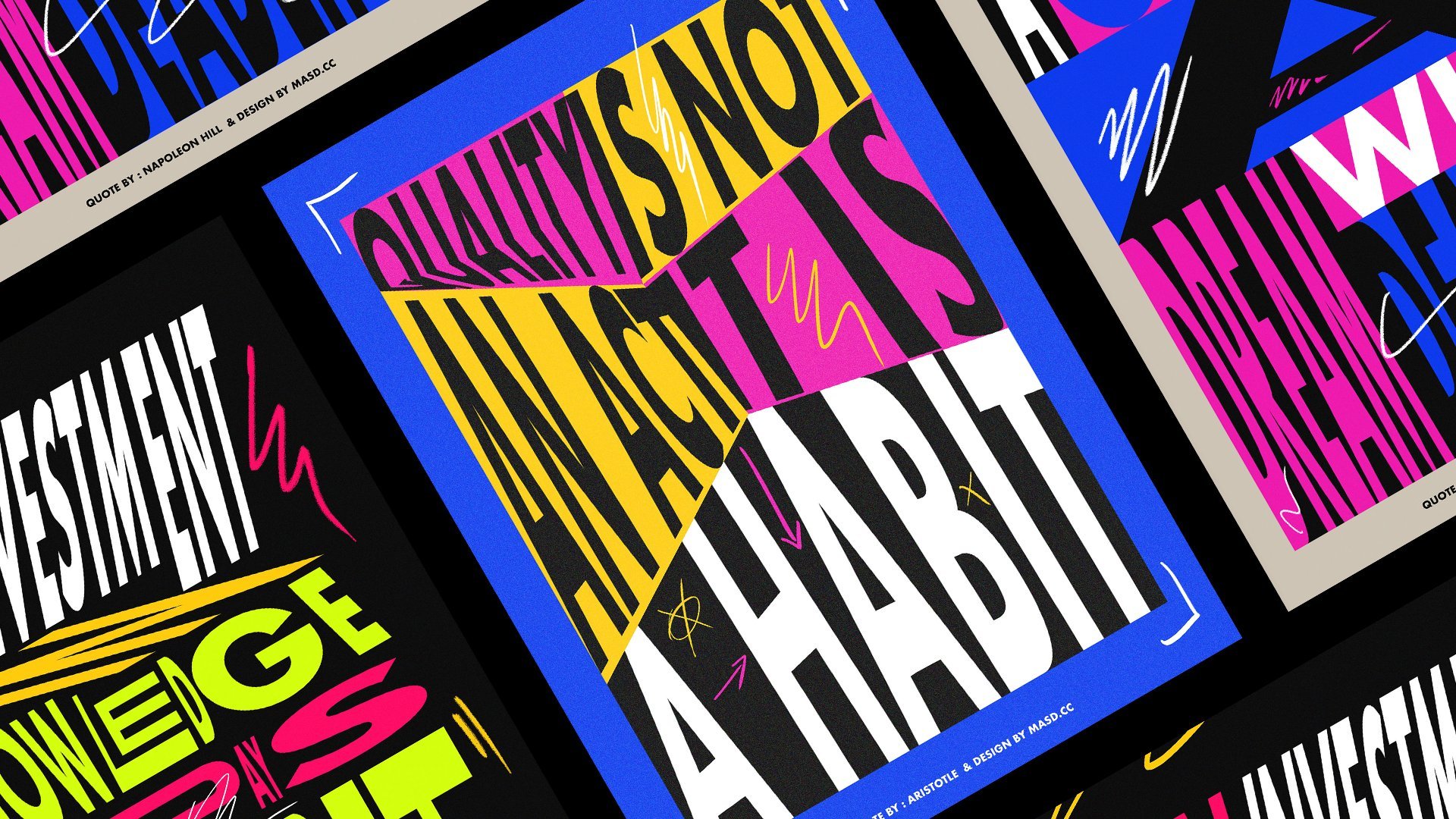
Conception d'affiches en typographie contemporaine
Introduction de classe - Inspiration et référence de style
Leçon 01 : Conception de la première affiche - Déformation typographique et composition de grille de base
Leçon 02 : Compostion menée par typographie - distorsion typographique individuelle
Leçon 03 : Composition d'affiche dynamique - Composition à base de distorsion et de forme d'enveloppe
Leçon 04 : Éléments de conception et post-production finaux dans Adobe Photoshop
Aujourd'hui, nous allons concevoir ces 3 affiches de typographie contemporaine différentes,
La plupart du design sera réalisée dans Illustrator en utilisant 3 techniques et approches différentes du design, puis quelques touches finales et concevoir quelques détails sur le photoshop
1. Bande-annonce du cours: Bonjour tout le monde. Je m'appelle Marcus, animateur animateur. Aujourd'hui, nous allons concevoir ces trois affiches typographiques contemporaines différentes. La majeure partie de la conception sera réalisée dans Illustrator en utilisant trois techniques différentes et trois approches différentes de la conception. Et puis nous ferons quelques touches finales et l'entonnoir. Ce sont des détails dans Photoshop. Je suis presque sûr que vous allez avoir du plaisir à faire ce tutoriel. Et je suis sûr que vous allez avoir de nouvelles techniques à mettre sur votre manche. Alors n'oubliez pas de vous inscrire et de me rejoindre en classe. 2. Introduction du cours - Inspiration et référence du style: Bonjour à tous et bienvenue à la première leçon. abord, je voulais juste partager avec vous d'où j'ai eu cette inspiration. C' est en fait ces affiches. J'ai eu ça. Je les ai vus sur Pinterest et ensuite je suis allé regarder. Qui était le designer qui a commencé ce genre de style. Et parce que je pensais que c'était vraiment cool et je voulais vraiment expérimenter avec ce titre aussi. J' ai donc aimé quelques affiches remplissant ça, faisant ce style. Et je voulais juste partager avec vous le portefeuille de designers. Il s'appelle Chris Andrew petit et c'est notre designer australien. Et dès que j'ai vu son travail, j'étais comme fasciné par l'utilisation de la typographie. Je n'aime pas la dernière, je crois, depuis un an environ. J' ai été obsédé par le travail de typographie. J' ai vu tellement de contenu sur Instagram à propos de la topographie cinétique ainsi que de la topographie mobile et de nouveaux types d' ondes pour utiliser la typographie normalement comme je l'ai fait avant la classe, comme la typographie, j'ai senti un elifs légers comme dans le monde du design vit dans un très, dans une sorte de strict vers comme monde sérieux. Et quand je vois quelqu'un faire, je m'amuse tellement avec la typographie et je fais vraiment si beaux dessins et je ne fais que briser toutes les règles. Comme, comme obtenir un type et juste déformé comme ça. Et expérimentez avec des couleurs et des contrastes entre les formes. Et puis il suffit de créer cela comme des compositions intéressantes avec elle. J' étais juste fasciné par son travail et j'ai juste décidé d'explorer un peu pour moi-même, quelques pauses tombant ce style peut-être essayé d' obtenir des connaissances sont libérées aussi parce qu'il Arctic est comme, n'est pas comme ça est correct de s'inspirer et parfois même de copier d'autres. Les gens, les designers travaillent parce que vous prenez comme vous avez essayé de recréer quelque chose. Vous avez essayé d'entrer dans l'esprit de cette personne et d'essayer de voir ce qu'elle voit. Et ce ne sera jamais le même parce que vous aurez toujours votre propre contribution à ce sujet. Ce n'est pas comme si je créais Saclay, celui-là. Maintenant, vous allez juste utiliser le même type de style, mais ce ne sera jamais la même voix parce que c'est unique pour vous, comme votre approche sera différente. Donc, il est correct si vous vous inspirez juste où d'autres personnes, je suis sûr que Chris, Andrew Coats inspiré par certains quelque part aussi bien. Tout comme un mélange de respirations et je voulais juste partager avec vous c'est le portefeuille d'abord parce que je pense que c'est vraiment, je ne pense pas que vous devriez le vérifier. Et je pense que c'est incroyable. 3. Leçon 01 : Concevoir la première affiche - distorsion et composition des mailles: Je vais donc montrer d'abord que les journalistes que nous allons concevoir. Donc, la conception finale sera sur un magasin. En fait, c'est comme les formes vectorielles. Et le premier que nous allons commencer est celui-ci. Une autre chose que je voulais partager avec vous est que j'ai créé une bibliothèque pour ce cours, va être sur vos fichiers Skillshare. Veillez à télécharger la bibliothèque. Vous aurez les couleurs et l'illustration réelle. Et pour cela, vous allez juste dans les bibliothèques ici. Si vous n'avez pas l'onglet de la bibliothèque ici, vous pouvez simplement aller à Fenêtre et essayer de trouver vos bibliothèques ici. Et puis nous allons juste à la bibliothèque d'importation. Sélectionnez la destination de votre bibliothèque. J' ai déjà sauvé le mien ici. Donc vous allez avoir ce fichier dans le dossier. Et dès que nous avons importé, il vous suffit de cliquer sur ouvrir et d'importer. Et tu auras toutes les couleurs que j'utilise sur ces affiches. Et les affiches réelles et réelles au cas où vous voulez les ouvrir et juste jeter un coup d'oeil. Si vous cliquez et glissez et déposez comme ceci, vous allez simplement le déposer. Si vous voulez aller à l'intérieur du vecteur, vous pouvez simplement sélectionner Intégrer. Et puis nous allons juste incorporer l'illustration ici et vous pouvez simplement dissocier puis relâcher le masque d'écrêtage. Et tout ce que vous avez maintenant est un fichier vectoriel. Et vous avez juste besoin de libérer les masques d'écrêtage jusqu'à ce que vous ayez réellement toute la capacité du fichier. Eh bien, commençons notre première affiche pour cette école de droit à nouveau. Nous allons vous montrer que cette résolution va réellement la rendre verticale 358 par 4961. C' est plus ou moins comme une affiche A3. Alors donnons juste un nom à cette affiche de Skillshare. Un. Et appuyez sur OK. Je suis désolé si je parle probablement trop vite. J' essaie de ne pas faire attendre trop longtemps cette classe. Je ne sais pas. J' ai l'impression que parfois j'aime être comme le grenier est plus dynamique si l'enseignement est encore tapé à la vitesse et ne prend pas trop à ces employés ou expliquer ou beaucoup trop lentement. J' aime le garder, reste génial moi-même engagé dans la classe. Donc, pour ces classes, j'utilise en fait quelques citations inspirantes d'un Moyen-Orient en fait, et je dois partager cela sur des fichiers sous. Et DC était comme quelques appels d'inspiration à l'avant, même des proverbes chinois, deux philosophes aux musiciens, aux intrapreneurs actuels. Et c'est comme je le fais, je fais la loi, je pense que c'est comme si il y avait beaucoup de pouvoir dans ces codes. Et parfois je les lis et ils font est comme Orozco pour moi. Parfois, je les lis et ils m'inspirent ou ont du sens à ce moment-là. J' aime donc en lire un au moins par jour et j'aime les utiliser autant que possible pour mon travail personnel, qui était ce que j'ai fait dans ces affiches. Donc le premier que vous allez utiliser vient d'un tas de Napoléon Hill. Et un objectif est un rêve avec un délai parce que vous ne voulez pas ce fichier. Ce sera dans le dossier Skillshare. Sélectionnez l'un de ces codes comme vous le souhaitez. Est-ce que j'ai essayé de ne pas utiliser de très longs parce qu'il vous donnera plus. Vous pouvez sélectionner aussi longtemps que vous le souhaitez. Mais plus vous avez de mots, plus vous aurez besoin de temps pour exposer chaque mot, ce qui pourrait être des meubles comme vous avez plus à expérimenter par tous, essayez juste de l'utiliser comme un très court pour l'instant. Et peut-être après avoir fait ce cours, même si vous faites ce type de style à nouveau, vous devriez explorer comme attendre plus longtemps pour sûr. Donc je vais utiliser celui-là. Je vais juste copier et coller ceci. Et je vais utiliser l'outil de texte dans Illustrator pour juste coller l'échelle de coin. Un rêve est un objectif. Un objectif est un rêve avec une date limite. Belle visite. Je vais en fait utiliser en fait un très bon, comme une cabine VLC de l'éthique est une police qui fonctionne comme vous le feriez n'importe quoi. Et quand je ne suis pas sûr du type de police que je vais utiliser pour n'importe quel projet. Et s'il est comme un projet client, 90 pour cent des fois ils auront déjà une police. Mais s'ils n'ont pas, je vais aller à sera vétérinaire soins ou coton ou pour la tournée. Et je vais juste aller au personnage ici. Et je vais tout faire. Donc, la première chose que vous devez faire est d'étendre vos tests, votre texte. Assurez-vous que vous êtes satisfait du code. Parce que dès que nous développerons cela, nous ne pourrons plus éditer le texte. Si vous voulez peut simplement faire une copie de cela, peut-être aller à modifier. Copier, Modifier, Coller. Laissez juste ici pour la sécurité au cas où vous voulez changer cela pour une raison quelconque ou changer la police. Alors commençons. Allons à Objet et allons à Développer. Appuyez sur. Ok, parfait. Donc le truc dans le style que j'aime le plus, c'est les laiteries, pas de règles sur la façon dont vous traitez sa police. Vous pouvez l'étirer vers le haut ou vers le bas. Vous n'avez pas besoin d'aimer, vous savez, quand vous concevez, vous devez vraiment être à la recherche du crénage et essayer de faire sens de la distance et tandis que les proportions et genre, c'est tellement ennuyeux parfois . Et le style est tout, mais pas une erreur ennuyeuse. Donc, la façon dont j'aime le faire est juste, commençons par séparer les mots. Un but est un rêve. Date limite. Super. Ainsi, vous pouvez en fait, si vous le souhaitez, vous pouvez commencer à créer des formes en premier. Et comme nous allons utiliser l'outil Rectangle, par exemple. Et juste essayer de créer des formes comme nous avons commencé, aléatoires. Vous n'avez pas besoin de suivre les notes. Nous pourrions faire une grille et suivre la grille, mais c'est pour être aussi libre que nous, comme nous le pouvons. Je pense que si vous pouvez tous le lire en tant que designer, nous avons déjà beaucoup trop de règles. Donc, nous allons savoir qu'il y a des règles ici et pas de grille du tout. Alors allons-y. Vous pouvez juste aller à la lumière que vous élaborez, tenir à juste important et utiliser mes couleurs si vous voulez. Sinon, vous pouvez simplement aller aux nuances de couleurs ici. Trouvez une très belle nuance pour votre affiche. J' aime le pape déchiré par la guerre. Et vous pouvez simplement explorer toutes les couleurs étonnantes qui se trouvent déjà dans les bibliothèques d'Illustrator. Ou vous pouvez simplement aller aux équipes de couleur et essayer de trouver une couleur vraiment agréable pour lui et juste utilisé à elle. Ne vous sentez pas obligé d'utiliser mes couleurs. S' il vous plaît, assurez-vous que vous l'êtes. Vous explorez en fait plus de couleurs et je vais essayer de ne pas passer beaucoup trop de temps sur les couleurs sur cette classe parce que je voulais faire une charge. Et, mais et je suis sûr que vous pouvez simplement utiliser cet explorateur sur la couleur, Adobe Color Thèmes sera, vous êtes prêt à aller. C' est une sélection incroyable ici. Je vais juste fermer ça pour l'instant. Alors commençons. Donc, vous pouvez juste commencer comme je l'ai dit, comme juste bloquer quelques formes autour et ensuite utiliser vos textes. Ils sont comme, je pense à peut-être comme cette forme noire ici. Je vais à la commande C, commande F pour coller en place. Je vais le faire utiliser cette couleur rose ici. Et maintenant je vais me faire perdre mon premier mot. Je vais faire ça large. Choisissons ce solide noir parce qu'il est devant une lettre et je vais l'arranger et le vendre à dos. Et ils vont utiliser cet outil de distorsion ici, l'outil de transformation libre. Si vous cliquez sur E, il suffit de vous pousser vers le haut. Ici. C'est, ça fait du bien de faire ça. Pour une raison quelconque. Si mes directeurs artistiques, certains font ça à notre, dans notre travail, elle va juste se montrer, juste me tuer. Je ne peux pas faire ça avec des polices. Mais le truc, c'est que, je pense qu'on devrait avoir le temps de jouer. Je pense que c'est quand vous arrêtez de jouer et de s'amuser avec le design est quand vous commencez, quand vous dites juste quand il commence à être juste un travail et pas comme un passe-temps ou comme en fait quelque chose que vous aimez faire ? Je pense que pour moi je n'ai pas joué pendant des années. Comme en tant que designer, je viens d'avoir du travail client et je l'ai fait a fonctionné parce que je ne sais pas, pendant longtemps sans faire d'expériences personnelles ou de projet personnel. Et je pouvais avoir l'impression que je n'étais pas Thai Wah commencer à haïr. Mais je commençais à ne pas profiter comme j'avais l'habitude de profiter de mon professionnel comme quand j'ai commencé. Donc, c'est un, Je vais juste faire glisser le but maintenant, faites un clic droit. Amenez-le à l'avant. Oui. Donc je pense que c'est important aussi pour vous, tout comme, vous savez, c'est important pour vous d'aller dehors et de vous promener dans la nature. Je pense que c'est important aussi, d'aller dehors sur Illustrator et juste avoir un, aller. Amuse-toi juste, tu sais ? Non, juste créer quelque chose. Ou même tout comme je l'ai fait, continuez comme sur Pinterest, trouvez quelque chose de vraiment cool et essayez de le recréer en quelque sorte et essayez d'en faire votre site, pour en faire votre style. Donc maintenant, comme je suis déformé est un peu, mais sur un but, je veux réellement commencer à déformer le briquet comme égal. Je veux en faire un peu plus. Peut-être que je vais faire l'un des distorsions individuelles comme. Au lieu d'être un groupe plus âgé. Comme ça. Peut-être que le o faire quelque chose comme ça. C' est peut-être que tu vas soulever cette jambe. Sont tous déformés encore plus qu'un, quelque chose comme. Donc, la première affiche, je veux juste demander d'explorer comme juste des distorsions d'échelle, pas comme autant de rotations. Et c'est comme un échauffement pour ce qui se passe ensuite. Donc un but est que je le ferai, je ne peux pas vraiment faire le simple, désolé que j'ai fait avant. Ça. Par exemple, je vous ai montré ici. Parce que c'est comme, ça, ça dépend vraiment du moment où vous faites ça. C' est comme chaque fois que vous allez faire ce processeur, il va recréer. Il aura un regard différent conçu de sorte que la technique sera certainement la même. Tout comme explorer les formes et les formes. Un but. Peut-être que vous pouvez simplement mettre à l'échelle ces jours-ci pour jouer avec le contraste liquide et la position ainsi. Tu sais, comme un but, tu n'en as pas besoin. Encore une fois, nous avons cette boîte ici pour, pour référence. Bien que nous le puissions, nous pouvons jouer avec la boîte autant que nous le voulons aussi. Vous n'avez pas besoin d'être trop précieux à propos de la boîte. Comme, encore une fois, nous ne voulons pas de grilles est comme des lignes directrices que nous ne pouvons pas suivre l'ère. Donc, un but est, nous allons juste faire maintenant est un but est un peu comme ça, mais sont en fait besoin de faire est de créer une certaine séparation entre les lettres. Sinon, on dirait qu'il est le même mot comme les gardiens de but, au lieu de deux moments différents du vocabulaire. C' est logique. Oh désolé, je viens d'utiliser un raccourci, mais vous pouvez simplement sélectionner la forme ici et organiser et envoyer à, vous avez le raccourci ici. Je vais juste envoyer à l'arrière et arranger. Envoyer à Retour. But est juste peut-être choisir, peut-être des changements trop larges. Peut-être que tu vas encore jouer avec la sphère de distorsion. S' il vous plaît assurez-vous de trouver comme obtenir comme un code vraiment sympa de cette liste et, et jouer autour. A vraiment envie de voir comme parce que je suis sûr que certaines personnes choisiront les mêmes codes pour. Vous pouvez même ajouter comme je l'ai fait en ce moment. Vous pouvez simplement ajouter de nouveaux éléments à leur police. Il n'y a aucune promesse. Erreur. Partez en disant que c'est comme si je suis sûr que certaines personnes choisiront le même, le même froid, l'outil Simcoe parle à différentes personnes. Et je veux vraiment voir comme, comment, comment allez-vous cela, comment vous le concevez, comment ce sera différent ou vous savez, comme comment quelque chose comme deux personnes peuvent avoir le même code et en raison de deux différents conçoit soigneusement. Et même le collège, je pense que les couleurs sur ces exercices sont si essentielles parce que c' est comme si vous jouiez avec le contraste et les formes et vous êtes certainement désordonné avec toutes les règles de la typographie. Mais la couleur aide aussi, comme aide le message beaucoup ici. Continuons à changer ça jusqu'à ce que ça se sente bien. La chose si un téléphone conçoit parfois c'est un peu comme si c'était un peu un sentiment. Parfois, c'est juste comme vous, vous sentez n'est pas encore là même quand ça a l'air beau. Continuons à pousser. Et puis est, alors vous date limite de ce qui est Est le fil est conçu et ce qui est l'art devient vraiment difficile à définir pour moi au moins. Parfois, je pense que le design est une combinaison de fonction et d'art. Et je ne sais pas si c'est une chaîne. Où est-ce ? Nike est blanc aussi. Peut-être que je vais déformer cette diapositive. Et encore une fois, vous, ceci, il s'agit juste d'expérimenter et de décharger tout. C' est comme si vous êtes un réalisateur, dit que c'est à propos de faire, ont vraiment faim ou Hey, je suis vraiment en colère. Comme quoi ? Ce que tu fais c'est l'objectif de décharge est correct, cool. Il suffit de pousser ça. Peut-être en fait, nous allons alors nous allons faire de cela un objectif est. Et puis peut-être que vous pouvez continuer à expérimenter jusqu'à ce que vous vous sentiez juste et que vous pouvez toujours revenir ici. Et la justice. Maintenant, nous allons juste utiliser l'échelle ici. Donc, c'est l'échelle d'utilisation. Oui, Donc, pour venir remplir plus mieux , celui-ci ici, c'est parfois difficile de jouer avec le contraste des formes aussi. Oui, je pense que tu penses que je suis content de ça. Et maintenant, rêvons. Donc jusqu'à ce que vous utilisiez le même style que j'utilise sur une première affiche, que j'utilise l'a pour remplir tout cet espace. Il crée une très belle forme. Et comme ce genre d'effet de flèche, ce qui est vraiment cool. Donc, je vais juste faire une nouvelle boîte ici en utilisant l'outil rectangle ici. Et je vais trouver une couleur pour ça. Peut-être que ça pourrait être bleu. Rose maintenant, filtre bleu, non ? Pourquoi ils ont l'air vraiment sympa ? Donc, quand on aura fini toutes les affiches, on les emmènera à Photoshop. Et là, nous allons le faire, ajouter un peu plus de détails, comme quelques gribouillons dessus alors. Plus comme plus de détails de bruit et ce qui rend cela un peu plus intéressant. Donc c'est bon si tu pars comme un espace vide comme celui-ci. Parce que alors nous pouvons, nous pouvons avoir plus, quelques détails sur un SharePoint il, comme vous allez le voir bientôt. Un but est un rêve. Le rêve est un rêve. Donc vraiment beaux mots qui appelle un rêve, mais je vais juste déformé comme ça appelé les yeux de Filson. Et même comme un, tu sais, comme quand tu fais ça, tu as l'impression de détruire en fait. Mais il est juste de rendre la déformation plus, plus intéressant est comme juste rendre cela plus utile à la, pour les yeux. Tu sais, c'est plus intéressant parce que si tu mets ça dans leur cadre blanc en utilisant Lake, comme ça, c'est bon, tu comprends le message et c'est important, mais quand tu fais comme ça, vous recevez le message et vous obtenez autre chose. Il y a quelque chose de différent. Tu as un autre sentiment de lettre. Tu vas le lire. Et vous éprouvez aussi une sensation ou assez sociale comme peut-être vous ne l'aimez pas, mais encore une sensation, semble comme un sentiment est la lecture et quelque chose de différent est non seulement la lecture est l'expérience d'un message. Je pense que chez Dream est un arbre. Je vais juste faire ça. Et peut-être une pièce de monnaie. Sois sûr que tu ne déformes pas trop. Alors vous perdrez la forme de la lettre. Vous avez encore besoin de comprendre que dire que je suis un et un sont autrement, alors vous, le message sera, ne sera pas aussi clair qu'il doit être, pour être en mesure de le lire pas rapidement, mais de le lire. Comme si tu ne voulais pas être comme quelque chose d'déraisonnable sur le seul A-frame. Sinon, vous pouvez simplement obtenir les intérêts pour le visuel, mais alors vous pouvez perdre l'intérêt pour l'information. Et l'information est aussi, est. C' est aussi important que, aussi important qu'un visuel. Je vais juste sélectionner ceci. Un objectif est un rêve avec une date limite. Encore une fois, nous avons une lettre a, qui est comme réalisé, cité parce que j'aime la parce que quelques flèche Osaka tout le temps. Nous ne résolvons qu'une police Attica. Et j'aime ce sentiment de pointer quelque part. Et la dynamique de l'un genre genre de cache-cache montre vraiment, eh bien. Je vais juste utiliser du noir. Parfait. C'est un rêve avec un délai. Je ne sais pas si je vais essayer ça. Peut-être que cela va créer comme un peu de bouche, plus de difficulté à comprendre ce qui est écrit ici. En utilisant un test comme celui-ci. Mais je pense que cela crée un beau, un beau visuel aussi. Je pense qu'il crée comme un joli nom dynamique et tableau parce que vous avez un objectif est un rêve. Et puis on descend avec cette date limite. Nous les bactéries partirons comme ça, assurez-vous de créer un fond solide. Rends-le blanc. Repoussez-le en arrière. But est un rêve avec une date limite. On peut peut-être jouer un peu à la composition ici. L' étoile à être sûr aussi, comme les distorsions personnalisées pour chaque lettre est qu'il crée comme une autre couche d'intérêts d'interprétation sujet sur elle. Comme les tirets vont à, peut-être que vous allez pousser le a et faire le n. Donc ils n'ont pas comme le, parce que quand vous les perturber complètement, il ils sentent toujours qu'ils sont des données comme ça. C' est juste leur style. Et quand faites-vous des distorsions différentes pour chacun d'eux ? Vous pouvez vous sentir comme, oh, c'est en fait un jour différent de rééchantillonnage. C' est peut-être un par un. Je vais juste repousser la date limite. C' est juste voir si ça marche. Maintenant, comme vous pouvez le voir, parfois cela fonctionne vraiment bien horizontalement. En fait, il a besoin de travailler aussi bien sur la verticale. Alors je vais peut-être le pousser comme ça. Alors je ne fais pas d'autre moyen. Oui. Donc c'est le premier. Et après avoir conçu l'affiche suivant ce genre de solution, j'aime un peu relâcher dans le pulsar de goudron et ensuite je vais simplement le regrouper. Et maintenant L, Lorsque vous bougez, il suffit de le sélectionner et vous bougez. Donc, tout à fait. La prochaine chose que nous allons faire est en fait de l'échelle un peu plus bas. Tuons comme 90 pour cent. Quelque chose comme ça. Je fais ça parce que j'aime vraiment signer ces affiches. Comme ce code l'était. Mettons comme froid par taille s'appelle Napoleon Hill. Donc, nous devons donner un certain crédit pour le, pour le code plus chaud. Citation de Napoleon Hill. Et habillez ce petit peu vers le bas. Peut-être 35. 35 ici. Faisons un design de Marcos. Et faites de même. Assurez-vous de donner du crédit à la, au créateur de code. Et encore une fois, donnez également le crédit pour la conception du portefeuille. Et assurez-vous de, si vous, si vous avez Instagram ou un peu jamais un réseau social, si vous postez l'efficace est s'il vous plaît assurez-vous de me tagger. J' aimerais voir et partager votre travail aussi. Mes, mes disciples. Et j'aime vraiment permettre vraiment quand, quand vraiment voir comme ce que vous faites quand vous publiez des projets sur la section projet de la classe ? Il dit, chaque fois qu'on a une notification et que je vois, c'est tellement sympa pour moi parce que c'est comme, oh, quelqu'un, ils le sont, quelqu'un a pris le temps de faire ce cours. Et j'espère qu'ils aiment chaque pars moi aussi voir le travail senior, tu sais, parce que c'est comme si ça rendait ma classe plus réelle pour moi d'une certaine façon. Alors faisons juste un ici. Allons juste aligner ça. Assurez-vous que vous n'en avez pas besoin. Eh bien, pourquoi pas ? Juste faire un petit arrêt là ? Oui. Donc oui, c'est notre première affiche faite. Nous aurons ce pulsar dans Photoshop plus tard quand nous aurons tous les pulsars d'arbre. Et puis nous ferons de la post-production en une seule fois. Donc, nous n'avons pas besoin de sauter de Photoshop puis de revenir à Illustrator. Faisons notre propre travail dans Illustrator maintenant. Et plus tard, nous avons sauté dans Photoshop. 4. Leçon 02 : Compostion à 02 - distorsion typographique individuelle: Salut et bienvenue à la deuxième affiche. Nous allons donc utiliser la même résolution qu'avant, 3008 par 4961 orientation verticale. Et c'est génial. Donc, la première refonte d'affiche, celle-ci, nous utilisons des formes pour nous aider à, à la composition des textes à l'intérieur de ces formes. C' est donc un bon exercice pour commencer, comme parce que c'est le cas, il est plus facile de trouver le bon équilibre. Nous façonnons d'abord, puis explorons les textes à l'intérieur de ces formes sur la deuxième littérature d'affiches. Donc ouvertement exemple ici, nous voulons réellement utiliser les textes comme, comme le centre principal de la composition. Comme nous n'avons pas de formes ici, nous allons jouer plus avec le poids du texte. Donc nous serrons, nous allions déformer un peu de textes, un peu plus. On va le faire tourner. Et toute la compensation sera guidée par le texte et la topographie. Alors, sautons. Donc Foster deux sont utilisés. Un autre manteau et encore est sur les listes. Je partage juste avec vous, désolé, et des intuitions. Mon cerveau commence à se geler parce que j'enregistre ces cours la nuit quand ma copine regarde la télé et que j'ai fini mon travail. Et je suis genre, tu sais quoi, je vais juste faire un cours de Skillshare. Et parfois, je suis un peu fatigante et mon cerveau s'arrête comme quoi, quoi d'autre dire ensuite ? J' ai essayé de faire des scripts pour ces classes, mais cela a empiré. Donc je ne le suis pas maintenant, je sais ce que je vais faire. Je fais la classe d'abord avec moi-même, puis j'ai essayé de recréer l'exercice. Et l'action se sent mieux parce que se sent événement plus naturel pour moi. Tellement désolé. Après ça, à part. Le quota que vous allez utiliser est un investissement dans le savoir, paie le meilleur intérêt de Benjamin Franklin. En fait, Benjamin Franklin, note de côté, est un être humain très intéressant. J' ai appris des trucs de santé comme dormir mieux et jeûner. Et Benjamin Franklin, c' était juste un incroyable comme la façon dont prendre soin de son cerveau et de son corps était quelque chose de fou. Et c'est vraiment un gars très intelligent, c'est sûr. Ainsi, un investissement dans le savoir paie les meilleurs intérêts. Skillshare est là pour le prouver. Faisons ce cours. Désolé, je vais arrêter de parler de personnel qui ne sont pas liés à la classe. Donc, nous allons juste à nouveau copier et coller ici. Un investissement dans la connaissance avec les meilleurs niveaux d'intérêt. Je sais que, en fait, je fais du design depuis moins de 10 ans. Et les meilleures choses que j'obtiens de ma carrière, c'est que le Times a appris d'autres personnes et des cours que j'ai suivis quand j'ai commencé ma carrière. Skillshare n'était pas encore une chose. Et j'avais l'habitude d'acheter des DVD DVD en ligne et o était si cher et nous échappe comme nous, moi et mes amis de l'université vont obtenir tout à fait. Et je pense que c'est une série qui coûterait comme quelque chose comme 200 euros de getNumWords, l'école d'effets visuels et pour After Effects. Et nous aimons aller ensemble et l' acheter ensemble, puis partager les DVD entre eux ? Eh bien, comme différents temps et 200 ans, il y a 10 ans était beaucoup d'argent pour nous. Encore beaucoup d'argent, mais c'était amusant et j' enseigne vraiment sur Skillshare parce qu'il est si accessible pour tout le monde. Et, tu sais, c'est comme si ça pouvait être quelque chose de vraiment en profondeur dans une technique, ou peut-être juste quelque chose qui devient vraiment amusant à faire. Et on peut le faire ensemble. Et je n'ai jamais eu comme ce genre de et même comme les tutoriels sur Skillshare sont plus expérimentaux et les années 1980, c'est quelque chose de vraiment intéressant pour moi parce que comme vous ne suivez pas à pas et vous nous avons tous le même résultat. En fin de compte, vous savez, avant que je pense que les tutoriels sont utilisés pour deviner, obtenir comme il y a 10 ans, les rendements suivent étape par étape. Vous aimerez un livre de recettes. Et à la fin, vous serez r aurait le même traversin ou le même design. Exactement la même chose. Et les cours que j'ai fait, fait sur Skillshare est surtout tellement créatif, est plus créatif orienté avec le noir. Vous pouvez apprendre une technique et profiter de l'exploration. Et je n'ai jamais vu deux personnes ont été plusieurs résultats. Alors commençons ça. Je suis désolé pour mon marmonnement maintenant. Je voulais juste partager ça avec toi. Bon, donc tout investissement dans le savoir paie les meilleurs intérêts. 70. Encore une fois, je financerai obtenir LV Attica. Un autre conseil est si vous avez déjà regardé le vieux documentaire Vertica, regardez il est, C'est vraiment incroyable. Et passons à l'objet et au plan x. Super. Cmt nous permet de sélectionner récompenses et de dégrouper cela et de mettre les portes à distance les uns des autres. Donc, vous savez, en fait, j'ai oublié de faire tout ça. J' ai fait un tas de commentaires. M. Et toutes les casquettes. Peut-être que non. Boulon. Je vais créer des contours. Vous pouvez cliquer avec le bouton droit de la souris et créer des contours, ou il peut aller à Objet et aller à Développer. Même chose. Et vous pouvez également voir le raccourci est Command Shift O et les contours que x est la plus grande chose que tandis que le logiciel il ya des millions de façons de faire une chose. Et nous allons investir dans la base de connaissances. Le meilleur intérêt. En fait, c'est déjà, pourrait déjà être quelque chose. Je pense que j'aime la façon dont c'est la dynamique des decks qui se passe ici. Un investissement dans le savoir, peut-être que la connaissance devrait être un peu plus bas. C' est comme un pas. Si vous aimez top quelques-uns offrir quelqu'un pas. Ok, mais ce n'est pas ce qu'on fait aujourd'hui. Donc, sélectionnons n et simplement en utilisant l'outil de transformation libre, Commençons à déformer cela pue d'abord, et poussons simplement celui-ci aussi. Donc, ok, allons juste, donc maintenant nous allons vraiment aussi gentils, n'avons pas de formes. Nous allons réellement utiliser le type pour créer des compositions dynamiques comme celle-ci. Juste va gagner vont juste tordre comme ça et puis peut-être jouer avec le n. Peut-être qu'il est juste pousser le N un peu. Comme en fait, voyons, voyons ce que les textes nous diront et l'investissement. Ok, je vois que ça se passe. Salut, Miguel. Poussez le N. Peut-être. Je vais juste faire ça. Ok, N'oublions pas d'utiliser les nouvelles couleurs si tu veux. Si vous ne voulez pas, s'il vous plaît ne vous sentez pas obligé de les utiliser. Et juste essayer de déformer ce truc. Encore une fois, juste avoir le plus de plaisir que vous pouvez. Comme personne ne regarde, personne n'est là pour vous juger. Je pense que pas été fou est la chose folle est juste de pousser cela vers le bas et d'essayer d'innover. Essayez de trouver la jambe droite. Composition que les techniciens radio ont essayé de pousser, dit, a essayé d'être en gras, vous n'avez pas besoin d'aimer, et sinon ne fonctionne pas dans la portée arrière note de départ. Donc une manière différente. Oui, peut-être que c'est une meilleure séparation entre le type et les lettres. Et je vais juste pousser ça. Maintenant, vous ne voulez pas perdre un vicieux aller à un investissement et juste essayer de faire ça. Vous pouvez également sélectionner les points à l'aide de l'outil de sélection. Si vous cliquez sur un aussi, ne vous pouvez pas simplement tirer ces points et nouveau, vous venez de déformer la typographie encore un peu plus. Et voyez jusqu'où vous pouvez réellement faire. J' ai une autre classe sur Skillshare et qui est que nous créons un formulaire différent en utilisant la police avant. C' est une topographie personnalisée de l'expérience, s'il vous plaît vérifier. Oui, je suis sûr que si tu avais aimé ce cours, tu n'aimerais pas ça aussi. Allons juste pousser ça vers le bas. Essayez de jouer avec cela comme en utilisant à nouveau ici. Peut-être qu'il suffit de pousser ça. Il y a un chef. Comme s'ils n'étaient peut-être pas là. C' est juste que parfois je ne veux pas me battre contre l'illustrateur suédois et c'est bon. Expérimentez peut-être en fait quand il y a un ici, je vais déformé t. Encore une fois. Assurez-vous de ne pas avoir peur de faire l'édition parce que c'est, Il est seulement des expériences que vous en fait, quand vous jouez est quand vous en savez plus, est quand vous en fait, vous pouvez prendre cela à l'avenir pour quelque chose totalement différent. Vous savez, comme quand vous apprenez que, comme une nouvelle technique que vous avez apprise dans cette classe, que vous pouvez utiliser réellement pour votre vrai travail ou la vie sont des exercices totalement différents, mais c'est quand vous explorez comme ici. C' est, on ne sait jamais où, où ça va t'emmener, ou quand tu vas vraiment l'utiliser, ou quand tu veux vraiment en avoir la chance. Imaginez que si vous avez la chance, quelqu' un voit votre affiche et dit, Oh, je le veux. Ce sera parce que vous l'avez explorée. Nous ne le serons pas parce qu'il est en vous le sera parce que c'est unique pour vous. Et c'est la beauté de ne pas faire un design traditionnel. Affiche des plats parce qu'il est devient unique, est devient différent et Garros plus d'attention. Donc, plus vous jouez, mieux c'est. Continuons à pousser ça. J' aime la façon dont cela, ce, ce treillis que j'aime travailler en gras ne sont pas vraiment, pas sûr de certains d'entre eux en fait, peut-être que le n est semble vraiment déformer ce peu plus. J' ai l'impression que nous perdons une certaine lisibilité et des investissements. Et encore une fois, c'est bon. Vous pouvez juste, vous pouvez simplement utiliser aussi quelques outils pour la distorsion de motif. C' est juste peut juste sélectionner ce groupe il. Donc outil de distorsion à nouveau. Oh sûr que vous pouvez juste jouer avec comme essayer de le déformer en utilisant notre outil de cisaillement ici, ou même comme notre outil de forme. Maintenant en fait va jouer avec ces outils de mouvements ici, l'outil de cisaillement je pense qu'il aide beaucoup chaque fois que nous voulons expérimenter avec une perspective différente sur cela, sur un texte. Comme si vous ne vous sentez pas vraiment satisfait de la position. Vous pouvez simplement jouer avec l'outil de cisaillement et voir où il vous mène. Surtout. Tu vas juste faire ça. Donc le A est assis là, quelque chose comme ça. J' essaie juste de jouer comme ça. Parfait et investissement dans, cousu dans est une grande chose et nous avons juste besoin de le faire. Parce que pendant que vous lisez ceci, vous voudrez être sûr de garder la, la séquence du code en cours. Donc, allons juste aller à n et juste jouer un peu trop il est, mais pas trop fou. On ne perd pas le sens de ce manteau. Comme ne pas signifier leur lisibilité de ce code. Désolé, un investissement. Connaissance. Donc le bruit en a un très grand. Peut-être qu'on peut jouer un peu plus avec la connaissance. Je vais juste pousser ça. Je viens de commencer. Poussez-le ici. Plomb. Je peux détruire individuellement pour rendre le texte un peu plus intéressant. Ne pas perdre totalement la forme de la lettre. Peut-être en utilisant une poussée. Oui, quelque chose comme ça. On peut aussi jouer avec la position des lettres. Donc, ce n'est pas une distorsion, mais aussi quelques compositions dynamiques avec la position des lettres est un investissement dans la connaissance. Voir comme, même comme maintenant, ça a l'air si dynamique et vous pouvez toujours le lire. Tu vas probablement prendre un peu de temps. Quand vous prenez plus de deux à cinq secondes pour le lire, peut-être que ça devrait juste comme je pense que c'est comme voir ce qui gêne. Ça ne t'aide pas. Dans ce cas. Je pense que le n, C'est peut-être un peu étain et nous perdons réellement la capacité de le lire comme la fin vraiment rapide. Et je vais probablement essayer de la rendre un peu lisible comme nous avant. Je vais juste sélectionner comme ça, peut-être utiliser notre outil de cisaillement à nouveau. Ou peut-être juste en fait va juste supprimer ce n. Je vais utiliser celui-ci ici. Et je vais utiliser celui-ci parce qu'il n'y a pas de problème à faire ça. Un investissement dans le savoir. Je pense que la connaissance et l'expérimentation, il y a beaucoup de connaissances parodontales dans l'expérimentation et les expériences, mais été, pas, eu peur d'expérimenter est certainement pas. Un investissement dans la connaissance, paie le meilleur intérêt. Encore une fois, je vais peut-être jouer avec p. Et je vais, en utilisant l'outil de sélection ici, pourrait pousser un peu ces points. Euh, un peu comme cette pièce clinique, une si belle lettre à jouer. Parce que c'est la forme de la lettre p est quelque chose comme Laker est comme un Tammy certains comme si ça a du sens, C'est juste comme un parapluie, un peu 5. Tu vois, tu peux mettre des lettres ici en dessous et ça a l'air vraiment sympa. Encore une fois, une distorsion individuelle comme celle-ci. Peut-être, peut-être pourquoi notre volonté de vraiment large peut juste bien. Split. Jouons avec l'élargissement comme ça, comme le chemin. Bien que je pense qu'on devrait jouer avec un peu de part sur ces lettres à coup sûr. Utilisons le cisaillement pour essayer de ne pas le perdre. Il suffit d'utiliser l'outil de distorsion gratuit. Et essayez de trouver une belle composition pour cela. D' accord ? Paye le meilleur. Voyez que c'est déjà une citation très semblable, un peu longue, ce qui me donne un peu plus de mal à tout reconfigurer. C' est pourquoi je vous ai dit si vous essayez de le faire, si c'est la première fois que vous faites cet exercice, assurez-vous d'utiliser comme un code plus court pour la première expérimentation. Donc, vous ne passez pas moins de temps faire la composition et plus de temps à jouer avec elle. Vous savez, parce que autant de lettres que vous avez, plus ce sera difficile. Donc, soyez juste au courant des données, en fait, soyez juste conscient que vous aurez probablement l'impression de faire cela pour la première fois. Sois conscient aussi. Pour essayer de trouver comme un code très agréable, facile à la, jouons juste autour. Voyez que vous pouvez, vous pouvez même étendre les lettres afin qu'elles se connectent réellement les unes avec les autres d'une certaine manière. La connaissance, la base de connaissances sont-elles le meilleur intérêt ? Donc les abeilles sont vraiment lettre intéressante aussi pour travailler avec. Donc c'est juste un intérêt est un mot très long, mais ça va être un bon rythme. La meilleure compétence cette pratique, jouer autour, il contraste. Comme vous pouvez le voir ici. Nous avons juste tordre une matrice très maigre ici et très audacieux B et T et cette mignonne comme peut-être à l'échelle ça. Jouez avec, avec le mouvement ainsi qu'une petite dynamique que vous pouvez faire votre achèvement, le mieux, le plus intéressant. Il regardera quelque part les yeux de quelqu'un d'autre, les intérêts. C' est un très long mot. Voyons ce qu'on peut faire. C' est que vous pouvez le garder aussi simple. Si vous, si vous le souhaitez, si vous avez l'impression que votre aversion est un code très long, et si vous avez envie d'ajouter plus de détails et de distorsion rendra les choses plus difficiles, vous pouvez juste, vous savez, je vais juste arrêter ici et juste faire un très, très simple. Pas comme, pas aussi fou. La composition, Nous, les destructions, base les meilleurs intérêts. En fait, ça va plaire. Il suffit de le pousser vers le bas. Encore une fois, déformez cela un peu plus en utilisant le L ici. Nice aux règles du terrorisme à nouveau, comme je l'ai déjà dit, vous continuez à expérimenter. Comme moi, je le fais, je vais vraiment aimer ça. J' ai l'impression que c'est un voyage conception de ce genre d'atouts parce que c'est une affiche, désolé. C' est parce que c'est comme si tu avais besoin que tu ne saches pas où tu vas. n'y a pas de moyen de définition. Il n'y a pas de ligne directrice comme Oh, le résultat final sera comme ça. Alors le résultat sera, s'il n'y a pas un moyen que vous pouvez savoir que cela dépend tellement du moment est un tel type de design actuel parce qu'il n'y a pas de livre de marque pour cela. C' est sur le terrain, c'est vraiment près de créer votre propre œuvre d'art personnelle ou dimanche. Je ne dis pas que c'est comme une farce ou quoi que ce soit. Je suis juste que je dis juste que c'est comme ça quand on crée quelque chose comme le design et les marques d'art. Et bien, j'aime, j'ai même aimé une première version Beck et White parce que c'est quand on a travaillé avec la typographie, il vaut mieux travailler avec la composition d'abord. Et pour cela, nous utilisons juste noir et blanc parce qu'il travaille entièrement en noir et blanc. Lorsque vous ajoutez de la couleur sera arrivé, vous savez, vous n'avez pas besoin de vous inquiéter. Donc, si vous êtes satisfait de votre version noir et blanc, optez pour la couleur. Maintenant, encore une fois, nous pouvons utiliser ma bibliothèque ici, ou vous pouvez simplement utiliser la vôtre et celles que vous avez choisies. Donc, en fait, va faire fond. Ici, je vais essayer d'utiliser les mêmes couleurs que j'ai utilisées auparavant. Donc on va essayer ça à l'envers. Sélectionné, Organiser l'envoi à l'arrière. Et nous allons rendre ce texte blanc pour l'instant. Même comme un inversé semble vraiment, vraiment sympa. Donc, nous allons juste diriger un peu de couleur dans ce design. Maintenant. Je vais sélectionner un lactose et sélectionner l'arrière-plan. Je vais ajouter cette couleur rose. Peut-être aurait-il pu, peut-être utiliser les mêmes couleurs mais pas dans la même séquence comme ça. C' est vraiment, c'est vraiment comme avoir ces coraux sont prêts à l'emploi parce que c'est, pour moi, c'est plus rapide faire ce tutoriel et de parler avec vous pendant que je fais ça. Parce que si j'étais vous, parce que quand je vais à la recherche de couleurs aussi, je voulais dire que je peux juste être passé comme deux heures, juste essayé de trouver un bel ensemble de couleurs ou en ligne ou juste obtenir une couleur. Et puis j'ai essayé de trouver une autre couleur qui correspond à cette couleur. Et puis je suis comme les couleurs des arbres et je ne les aime plus. Et c'est pourquoi j'ai déjà fait cet ensemble de couleurs ici. Donc je ne vous emmène pas dans ce voyage fou de moi essayer de faire une palette de couleurs pour moi. Ok, alors gardons juste le savoir. Je pense que je vais vivre la connaissance blanche. Je vais payer Pacer pour le rendre rose. Collez la basse. Je vais vous dire un secret. J' ai juste, J'ai juste aimé faire ce genre de design et j'ai tellement aimé ce style parce que je travaille actuellement pour une entreprise. Ce n'est pas comme si mon travail était ennuyeux ou quoi que ce soit. Il est juste que nous devons suivre les directives de la marque de l'entreprise. Tu peux aller comme ça sans raison. Mais parfois c'est un peu strict. Et quand vous devez suivre comme un livre de marque, vous devez rester cohérent. C' est comme si tu pouvais faire quelque chose de totalement différent. Il doit faire partie de, il doit faire partie de la marque de l'entreprise. Cet exercice m'a fait me sentir soulagée mais libre d'une certaine façon. Comme si je pouvais faire ce que je veux et je peux déformer la topographie comme ça parce que c'est comme la minuterie que vous passez à régler. Ses États-Unis. C' est beaucoup. Et c'est comme libérer votre gamme. Rage sur la typographie. Ouais, un peu comme ça. Euh, un peu comme la façon dont vous pouvez lire de deux façons différentes. Vous pouvez le jeter comme l'investissement, le meilleur, connaissance, les intérêts, puis n base. Mais la chose est comme vous, quand vous avez comme les couleurs et le noir est blanc, vous toujours, votre cerveau ira toujours d'abord aux blancs quand ils, puis va à la couleur la plus contrastée. C' est comme la théorie des couleurs. Et comme on l'appelle les valeurs des Blancs et des Noirs. Et vous allez toujours lire les valeurs d'abord et ensuite nous allons, vous, vous, vous lirez la saturation plus tard. Donc, il est comme d'abord lire les valeurs, qui est noir et blanc, et puis vous le ferez, vous allez lire les couleurs. Et cela crée une mise en page détendue, intéressante parce que c'est comme si vous pouvez lire cela, comme les connaissances et les touristes, ravageurs de l' investissement et paie dans le, c'est, c'est vraiment comme, c'est un vraiment sympa façon d'attirer l'attention. Pour le principal. Le message principal que vous voulez est que vous voulez transmettre des connaissances et des intérêts. Et parfois vous avez comme sur votre flux Instagram ou sur votre travail, vous n'avez qu'une fraction de seconde pour attirer l'attention de quelqu'un. Et en utilisant la théorie des couleurs, c'est vraiment important de le faire. Donc, ils s'arrêtent réellement ou même s'il ne s'est pas arrêté, le message principal que le message le plus important vole dans leur esprit. Au moins. Je suis désolé, je parle juste de théorie des couleurs maintenant. Et oui, c'est possible numéro deux. Et l'affiche suivante sera arbitraire et la dernière. Et après cela, nous allons finir où nous allons faire de la post-production dans nos affiches et exporter nos fichiers finaux. Et puis dis au revoir. Mais il reste encore une affiche à aller, alors ne partez pas. Je te vois dans la classe suivante. 5. Leçon 03 : Composition d'affiches dynamiques - distorsion et forme: Alors l'arbre du numéro d'affiche et ok, allons-y, juste aller à mes listes de citations. Et celui-ci est par Aristote. La qualité n'est pas un acte. C' est un abbé. Alors, allons juste à notre sélection de notre texte ici. Et encore une fois, la qualité n'est pas un acte, est une moyenne. Et essayez comme doula du mieux que vous pouvez. Et nous chronométrons le mieux que vous pouvez, ça va aller mieux. Et maintenant, je vais juste élargir comme nous l'avons fait avant. Donc, combien tu aimes, la façon dont tu dois faire, c'est que nous devons voir combien de mots nous avons. On en a un ici. Juste faire cela, juste pour l'exemple. Maintenant, les qualités, un mot est un autre, pas un autre. Donc, vous devez récompenses. Ce serait pour le nombre de formes que nous devons concevoir sur ce cadre ici. Pour. Tu n'as pas besoin de faire ça. Je fais juste pour l'exemple. Mais tu sais, tu peux le faire si tu as 67 ans. Je veux le faire comme un mot donc c'est le numéro carré. Donc maintenant ce qu'on va faire, il utilise notre stylo ici. Vous allez concevoir aussi aléatoire que possible. Quelques formes. Utilisons simplement, je vais utiliser mes couleurs ici à partir des bibliothèques que je partage avec vous. Et je vais le faire. Et celui-ci sera pour la qualité. En fait, nous allons juste faire glisser la qualité ici et arranger, porter à l'avant. Assurez-vous de grandir période. Lettres déjà groupées. Maintenant, sélectionnez-les. Cliquez droit. Ça ne me montre pas ça, va t'opposer et les regrouper. Cool. Et puis encore ici, a essayé d'utiliser les mêmes côtés de l'autre place. Vous pouvez faire quelque chose de différent si vous voulez, mais rendons les choses faciles pour l'exemple, il ne va pas réellement utiliser ces deux mots. Organiser, porter à l'avant, Objet, Groupe. Maintenant, allons-y comme ça. Ça va le rendre bleu. Et ce sera pour un acte. Je ne pense pas que je prendrais le coma parce que je te frappe comme une compagnie. Vous ne pouvez pas le supprimer plus tard et organiser, apporter à l'avant. Peut-être que tu vas rendre ça plus intéressant. Cette forme de plus est comme ça. Rends-le jaune. Peut-être. Gardons-le comme ça. Et puis Abbott sera à l'intérieur de cette forme bizarre. Il doit y avoir du noir. Allons juste passer par ça. Vous pouvez simplement sélectionner les lettres et appuyer sur Commande J ou Control Z. Ou vous pouvez simplement aller à l'édition ici et cet objet ici et ce groupe, les éléments ensemble. C' est un abbé. Une autre chose que j'ai essayé d'apprendre. Je scrute les meilleures habitudes de ma vie, mais c'est vraiment difficile à habiter. La création est une échelle qui travaille encore sur elle. Et d'accord. Donc oui, nous devons partager, les récompenses autour de ces formes que nous venons de créer. Et la prochaine chose que nous devons faire est juste en fait de dupliquer cette forme. Vous allez à l'objet, désolé, Modifier, Copier, Modifier, Coller en place. Et un injuste. Maintenant, juste sélecteur en fait. Et allez à Copy. Et maintenant, en sélectionnant le à la forme et le mot, nous allons à l'objet, puis nous allons à Enveloppe Distort et nous faisons réellement besoin d'organiser cela. Apporter à l'avant est une enveloppe d'objet déformer et faire avec l'objet supérieur. Comme il le fait, il utilise l'objet supérieur pour créer une destruction entière. Et nous pouvons juste revenir en arrière et coller, coller en place et renvoyer cela, arranger, renvoyer à retour. C' est des aides parce qu'il utilise l'extrême de la file d'attente pour créer un égaliseur. C' est le système entier comme s'il ne touche pas ici parce que cela en utilisant la file d'attente. Mais si vous le souhaitez, vous pouvez simplement aller à Objet et Développer. Et puis vous pouvez juste commencer est par vous-même si vous voulez, vous savez, comme juste le trier à la main si vous voulez, si vous êtes vraiment précieux, acheté pour six de son exemple, je ne vais pas le faire parce que cela prendra un peu plus de temps. Et je suis sûr que tu en as marre de m'entendre parler d'histoires et de ne pas t'expliquer quoi que ce soit. Maintenant, blague. Je suis sûr que je t'explique des choses et que je fais tout ça. Faites une copie et sélectionnez-les tous les deux. Objets. Faire avec l'objet supérieur. Et encore une fois, coller en place. Arrangez, envoyez à l'arrière. Est la qualité, n'est-ce pas, désolé, à la recherche de mensonges. Et est en fait c'est probablement le plus cool et le plus rapide sur la, sur la série. Et j'aime vraiment ça. Allons juste arranger ça. Amener à l'avant sélectionné Modifier la copie. Assurez-vous de la copie, sinon vous allez le charger dit objet, faire avec l'objet supérieur, en fait la virgule dedans. Et puis je vais juste faire la base en place, envoyé à l'arrière. Et c'est un arrangement ? Apportez à l'avant, Modifier, Copier, assurez-vous de le copier et aller à l'enveloppe distorsion faire avec l'objet supérieur et l'objet. Éditez, collez en place, organisez et renvoyez-le. Parfait. Maintenant, sélectionnons le dernier mot, Abbott et moins. Assurez-vous juste de ces groupes. Et les groupes, oui, vis. Voyons nous porter ça, aller le commander parce que je suis inquiet pour cette forme. Mais on ne sait jamais. Synthase, avant, Transformer, Organiser, Porter à l'avant. Faites une copie et vérifiez. Le maillage. Objet supérieur. C' est différent. C' est parce que l'ADA avait raison. Oui, j'ai fini par travailler très bien. En fait. J'aime vraiment que c' est comme si on se sent comme une affiche MTV de quelque chose de quelque sorte. En fait, on va changer la couleur de celui-ci. Allons seulement deux, rose. Parce qu'il a juste remarqué que j'ai utilisé le bleu comme bordure. Et je vais regrouper ça, les sélectionner tous les deux. Il suffit d'aller à l'objet, dissocier, ou simplement d'appuyer sur la commande G. Aller à l'échelle. 90 pour cent. Parfait. Et nous avons en fait oublié de le faire dans l'affiche numéro deux, qui est donné les crédits pour le code et pour le design. Mais je vais juste faire une pause pour le numéro 1, aller chercher x d'ici. Colle-le ici. Je vais faire froid par le grand philosophe Aristote. Et le design où Marcos. Et nous allons nous assurer que le second est également entièrement crédité. Nous allons juste peut-être groupé est lipide de la peau. Poussez un peu vers le haut et obtenez un nom fou ici. Alignons ça. Où est mon outil d'alignement ? Il y en a. Et nous allons définir ce code. Je ne me souviens pas de Benjamin Franklin, bien sûr. Sauf si juste collé Benjamin Franklin et conçu par Marcos. Et assurez-vous de vous crier avec votre nom. Tu n'as pas besoin de mettre mon nom. D' accord. Juste Jokey. Parce qu'un jour, mon école pour faire défiler a copié l'autre test grossier. Et elle a copié Sowell le test qu'elle a même copié à travers le nom de la fille. J' étais si drôle et c'était quand j'avais 12 ans ou quelque chose comme ça. Je me souviens encore de ce jour-là parce que c'était tellement embarrassant pour elle. Donc tu n'as pas besoin de copier mon nom. Et c'est ça. Nous avons donc nos affiches d'arbres qui les sélectionnent, les assemblent. Vous pouvez donc jeter un oeil aux trois impulsions que nous venons de créer ensemble. Et porno ne va pas filtrer. Et en fait, ils sont vraiment comme eux beaucoup. Et la prochaine étape que nous allons faire est d'apporter ces trois impulsions dans Photoshop, où nous allons faire quelques éléments de film de post-production rapide, le design. Ils utilisent des pinceaux. Et puis ils sont prêts à aller pour vos médias sociaux et à montrer à votre mère, le petit ami ou la petite amie. Tu sais, ton chien. Si vous avez un chien ou un chat ou n'êtes tout simplement pas là et gardez-le pour vous-même et nous ne parlons plus de cela. Donc j'essaie juste d'être drôle, c'est que j'ai essayé d'être drôle avec eux quand il glisse. Ok, donc je te vois dans la prochaine classe où on va à Photoshop. 6. Leçon 04 : Éléments de conception finaux et post-production dans Adobe Photoshop: Alors c'est tout, le moment est arrivé, et nous allons prendre ce processus dans Photoshop maintenant. Donc, je vais juste sélectionner ces affiches ici, et faisons juste une commande C ou aller à Modifier et faire une copie. Et passons maintenant à notre application quatre Shop Now. Donc Adobe Photoshop, j'ai déjà des préparateurs de plans de travail, mais je vais en faire un nouveau ici pour que je puisse vous montrer quelques petits détails au cas où. Donc, lorsque vous sélectionnez quelque chose dans Illustrator, lorsque vous allez dans Photoshop et que vous essayez d'obtenir un nouveau document, il sera quelque part que vous reconnaîtrez cette gauche de la taille du fichier. Et si tu as de la chance, je crois, je ne sais pas si ça arrive tout le temps. Alors n'aie pas peur si décent t'est arrivé. Ils feront déjà une spécification de fichier de plan de travail à partir de l'image désélectionnée auparavant. Donc, avec cette image sélectionnée, nous allons juste appuyer sur OK ici. Donnons juste un nom à ces mitaines de partage de compétences. Je vais faire tout l'arbre poser ensemble dans le même fichier Photoshop. Ce qui fera, parce que dans, si j'avais comme quelques détails de grain, je peux juste dupliquer la couche et ensuite utiliser la même couche au lieu de couper à chaque fois un nouvel effet. Donc j'allais juste les mettre tous en tant que lui des plans de travail Photoshop. Alors, nous allons juste des affiches Skillshare. Et c'est juste le nom, pas juste ça va. Et appuyez sur. D'accord. Parfait. Maintenant, je vais retourner à mon Illustrator. Je vais le sélectionner, assurez-vous de le copier. Et je vais éditer dans Photoshop et aller dans le collage. Ici vous pouvez sélectionner un objet intelligent, un chemin de pixels, un calque de forme. Donc l'objet intelligent est vraiment cool parce que vous pouvez juste, il suffit de le coller. Et ce qu'on va faire, tu auras cette icône ici. Et puis, si vous cliquez deux fois, vous revenez à Illustrator et vous pouvez simplement modifier votre fichier à nouveau, puis l'enregistrer et sera mis à jour dans Photoshop. Donc je passe juste entre l'application. Désolé, je fais juste mon clavier, donc je suis désolé si je n'ai pas expliqué ça. Retournons à Photoshop ici. Et faisons les premiers détails de cette affiche. La première chose que je veux faire est de créer un nouveau calque. Et je vais nommer ces détails de conception. Et donc la façon dont il est, ce design est, est vraiment rude. Comme vous pouvez le voir, nous ne l'avons